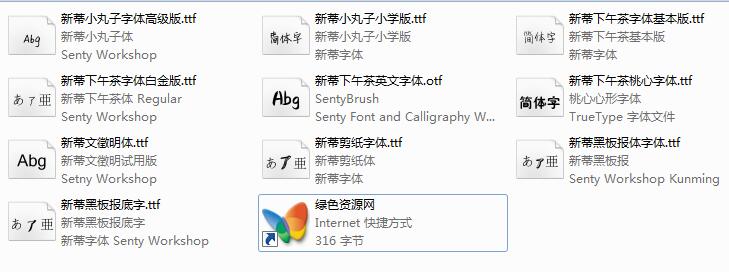
1.新蒂剪紙字體:可以輸出像剪紙版的字體效果,字體華美,富有藝術(shù)感!
2.新蒂黑板報(bào)字體:主要適用于黑板報(bào)字體設(shè)計(jì)使用!字體看起去美觀大方!
3.新蒂下午茶體專業(yè)版:提供了風(fēng)格一致的拉丁字母和數(shù)字,涵蓋的常用的低頻人名用字,如:玥堃珺曌偲禇瑨珣姼曈昳等(部分字只在專業(yè)版覆蓋)
4.新蒂下午茶體白金版:收錄字?jǐn)?shù):11000+;可以用于設(shè)計(jì)商業(yè)稿件,永久推送免費(fèi)更新!
5.新蒂下午茶體基本版:涵蓋常用漢字:4735滿足非專業(yè)使用者的日常需求,可免費(fèi)下載使用!
6.新蒂小丸子體-小學(xué)版:從原來(lái)的4800字增加到了7600+常用漢字;排版更加整齊;包括英數(shù)和全角標(biāo)點(diǎn);依然免費(fèi)!
7.新蒂小丸子體_高級(jí)版:從原來(lái)的4800字增加到9980+常用漢字,添加數(shù)量超過(guò)原有字總和;涵蓋了常用的簡(jiǎn)體字和繁體字;排版更加整齊;包括英數(shù)和全角標(biāo)點(diǎn);永久升級(jí)!